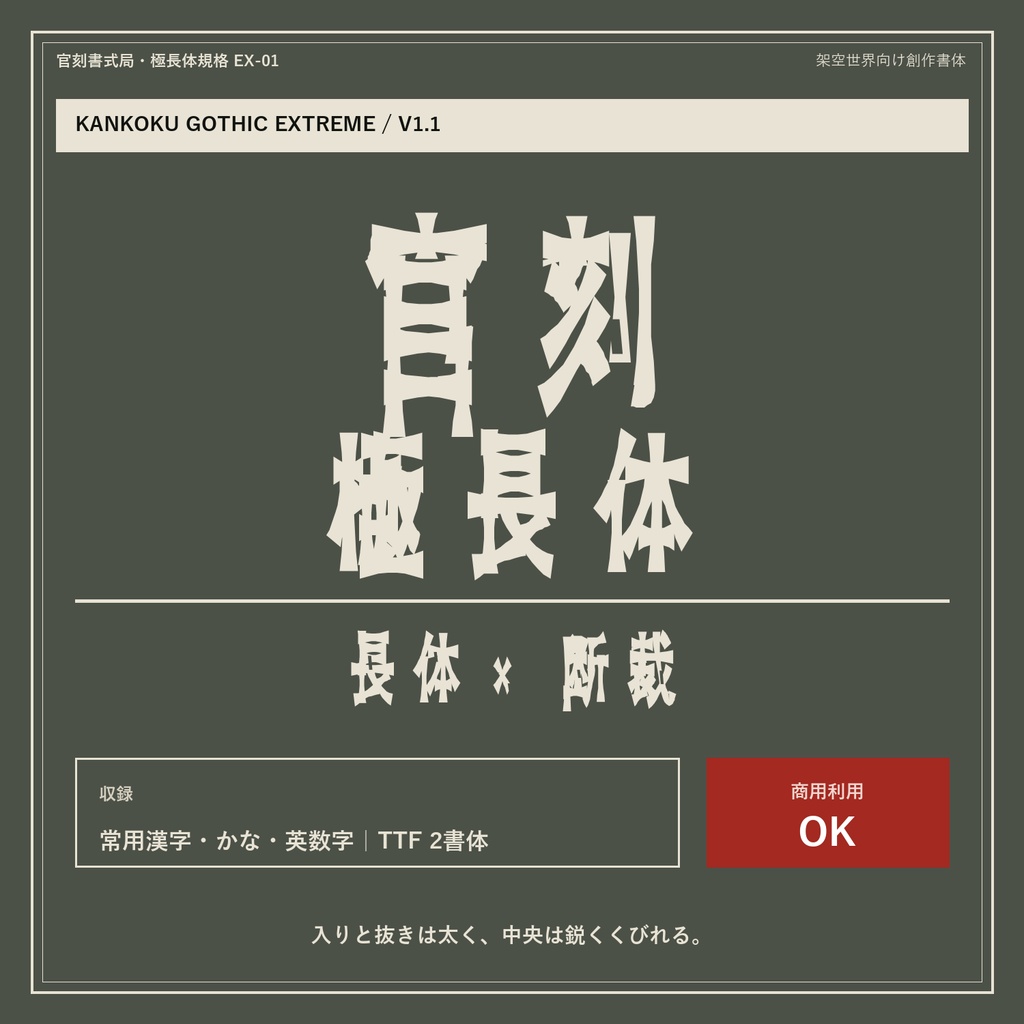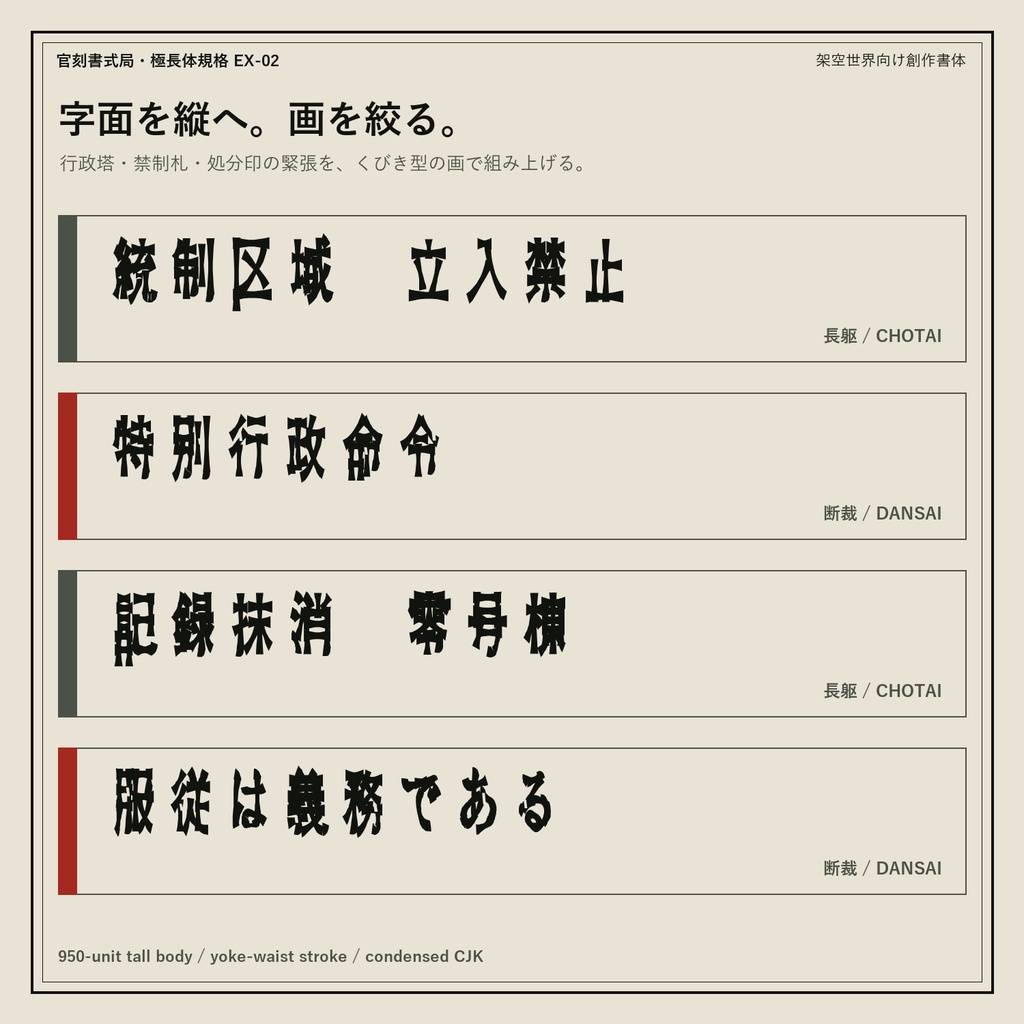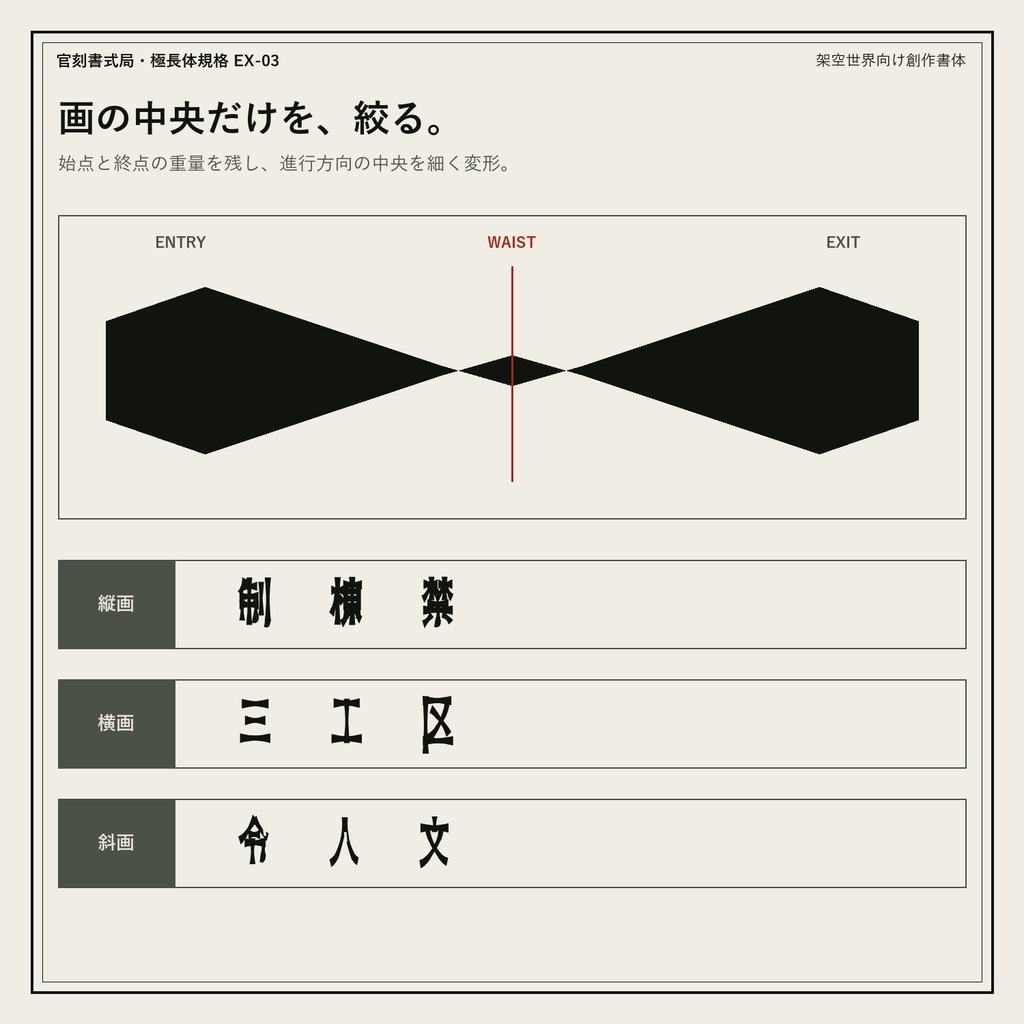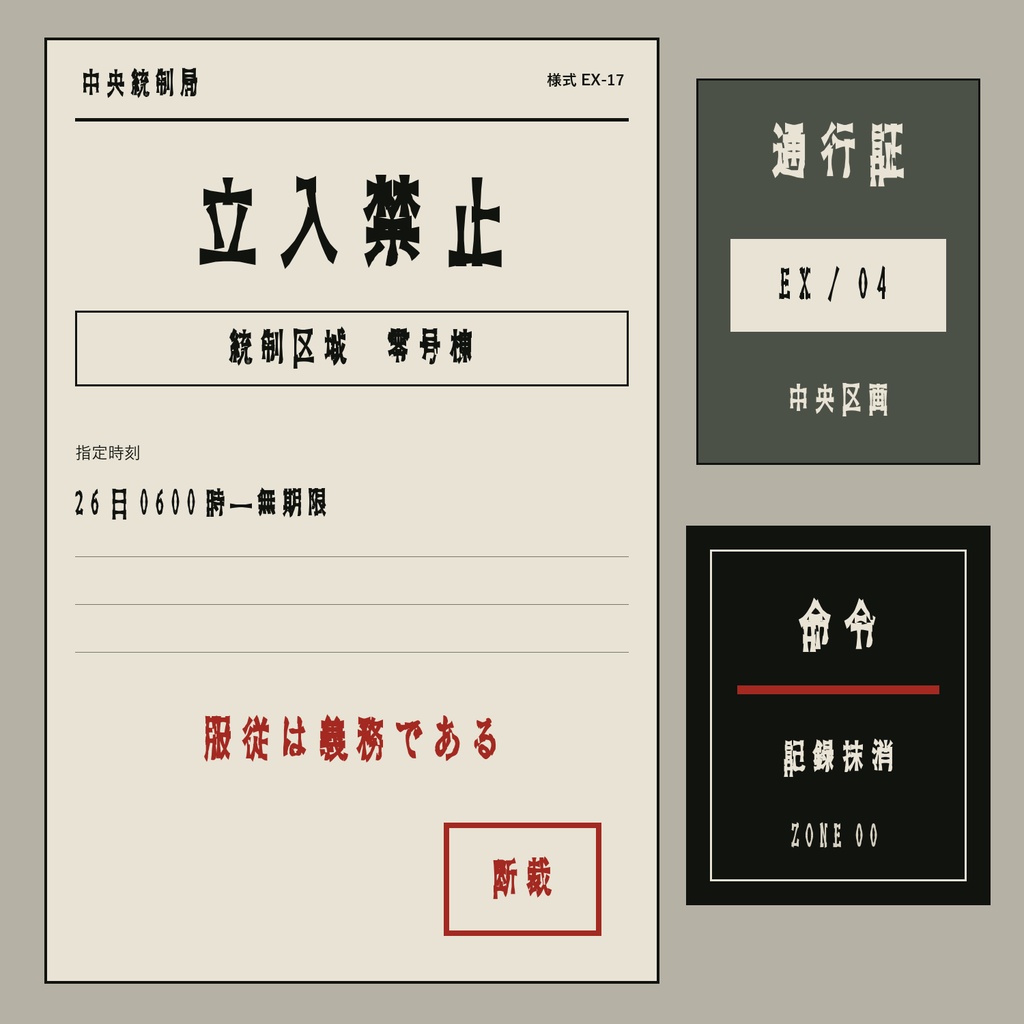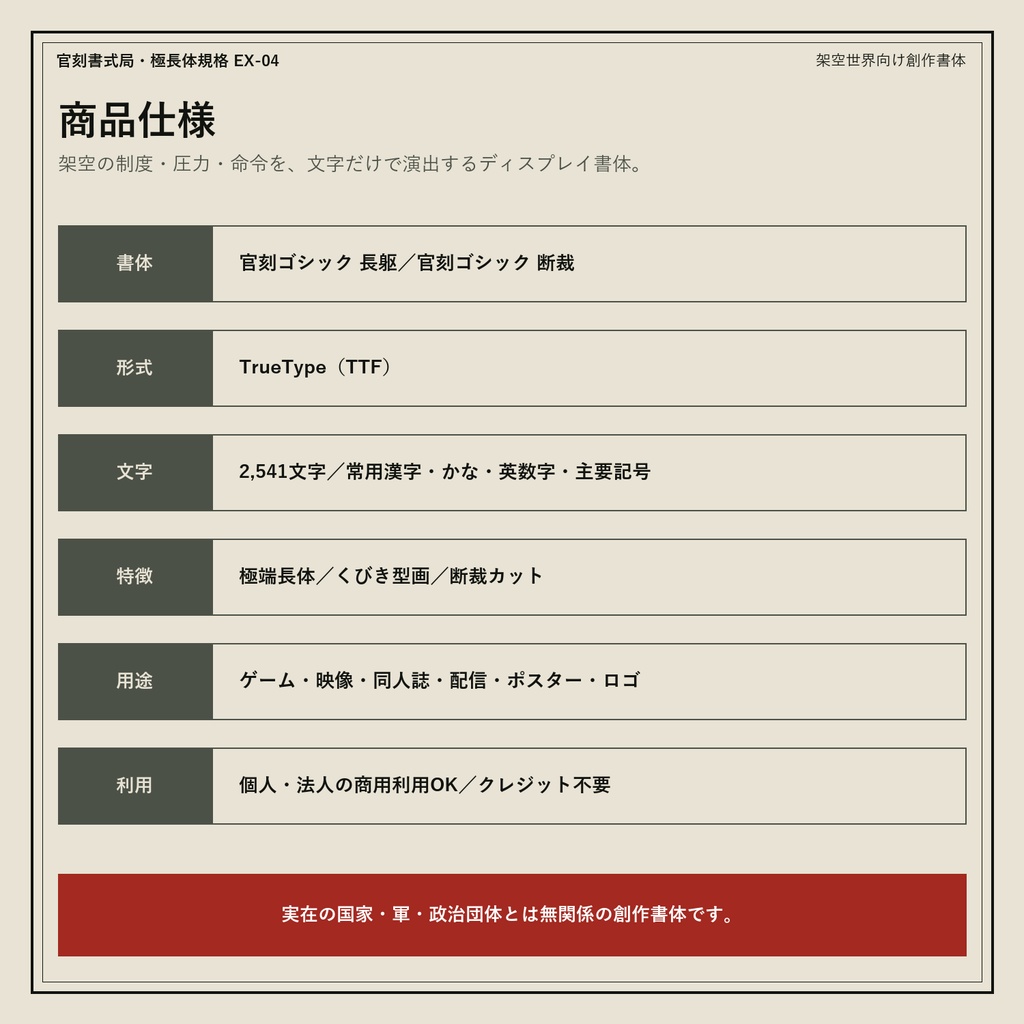
【極端長体×くびき型】官刻ゴシック 極長体|日本語フォント2書体・商用利用OK
入りと抜きは太く、中央は鋭くくびれる。 「官刻ゴシック 極長体」は、架空の行政国家・統制区域・命令書・禁制札をイメージした日本語ディスプレイフォントです。正方形の安定を捨てた950ユニットの縦長字面と、画の中央だけを絞る独自のくびき型処理により、細身でありながら異様な圧力を残します。 【収録】 ・長躯 / CHOTAI:くびき型の画を備えた基本カット ・断裁 / DANSAI:抑制した楔状欠損を加えた異形カット ・各2,541文字 ・常用漢字、ひらがな、カタカナ、英数字、主要記号 ・TrueType(TTF) 【おすすめ用途】 ゲームUI、架空文書、ホラー・ディストピア作品、同人誌、映像タイトル、配信画面、ポスター、ロゴ、TRPG資料。 【利用条件】 個人・法人の商用利用OK。クレジット不要。フォントファイルそのものの再配布・共有・転売、Webフォント公開配信は禁止です。無料体験版で、かな・英数字・使用例漢字を実際に入力して確認できます。 ※実在の国家・軍・政治団体とは無関係の創作書体です。